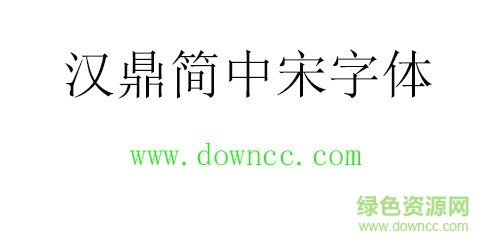
漢鼎簡(jiǎn)中宋體是一款應(yīng)用于平面設(shè)計(jì)、文學(xué)創(chuàng)作、平面廣告等領(lǐng)域的漢鼎字體,字體結(jié)構(gòu)勻稱,字形神韻超逸,非常適合朋友們?cè)趧?chuàng)作書法內(nèi)容的時(shí)候使用,而且還是永久免費(fèi)的哦,但是只限于個(gè)人使用,喜歡的小伙伴趕緊下載收藏吧!